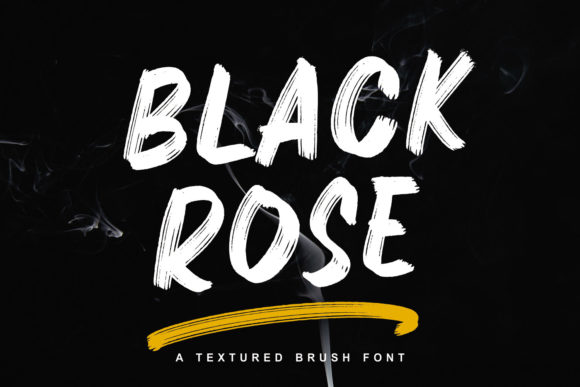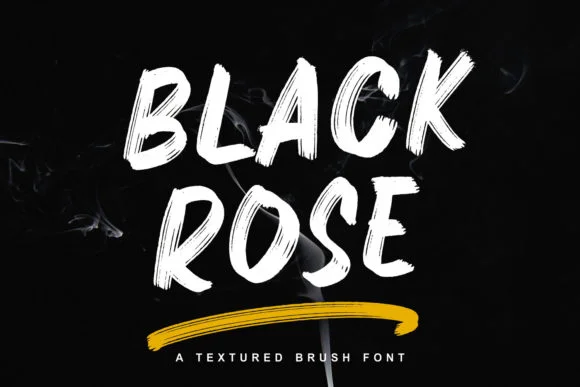
[Creativefabrica] Black Rose Font (2021)
Название: Black Rose Font (2021)
Black Rose - это крутой, смелый и матовый шрифт.
Этот шрифт подходит для дизайна футболок, спортивной одежды, логотипов, рекламы, одежды и многого другого.